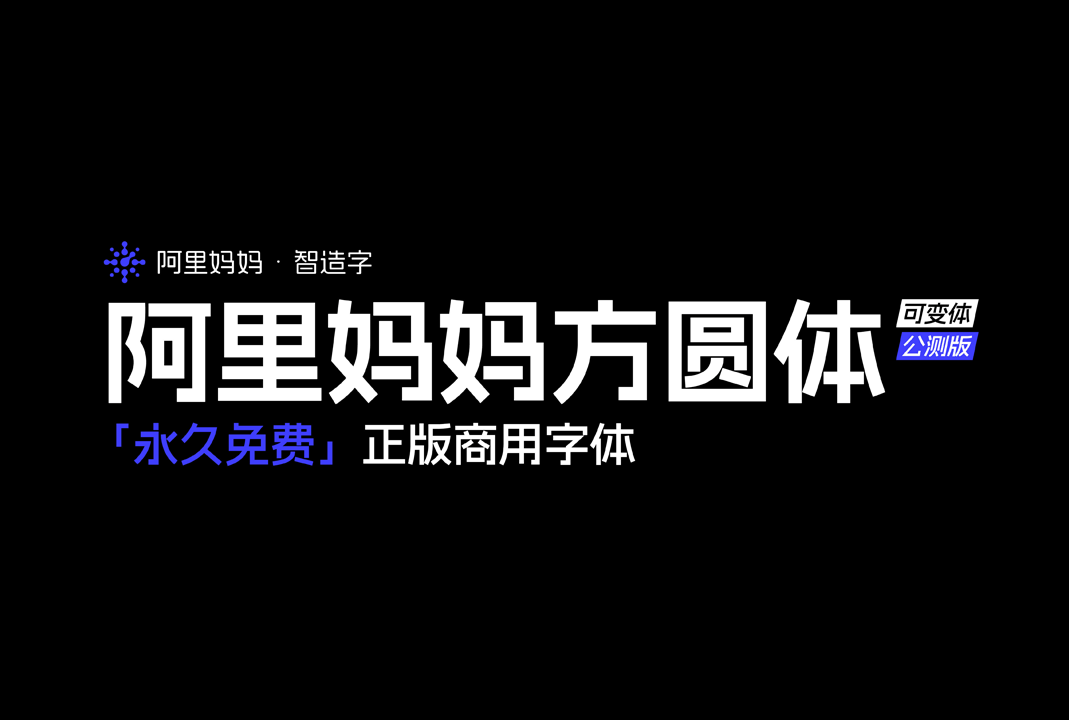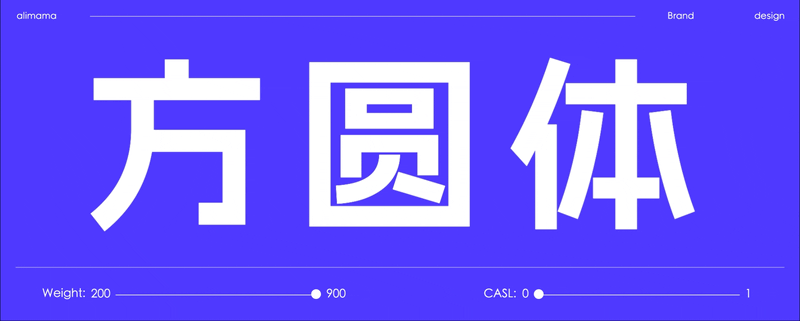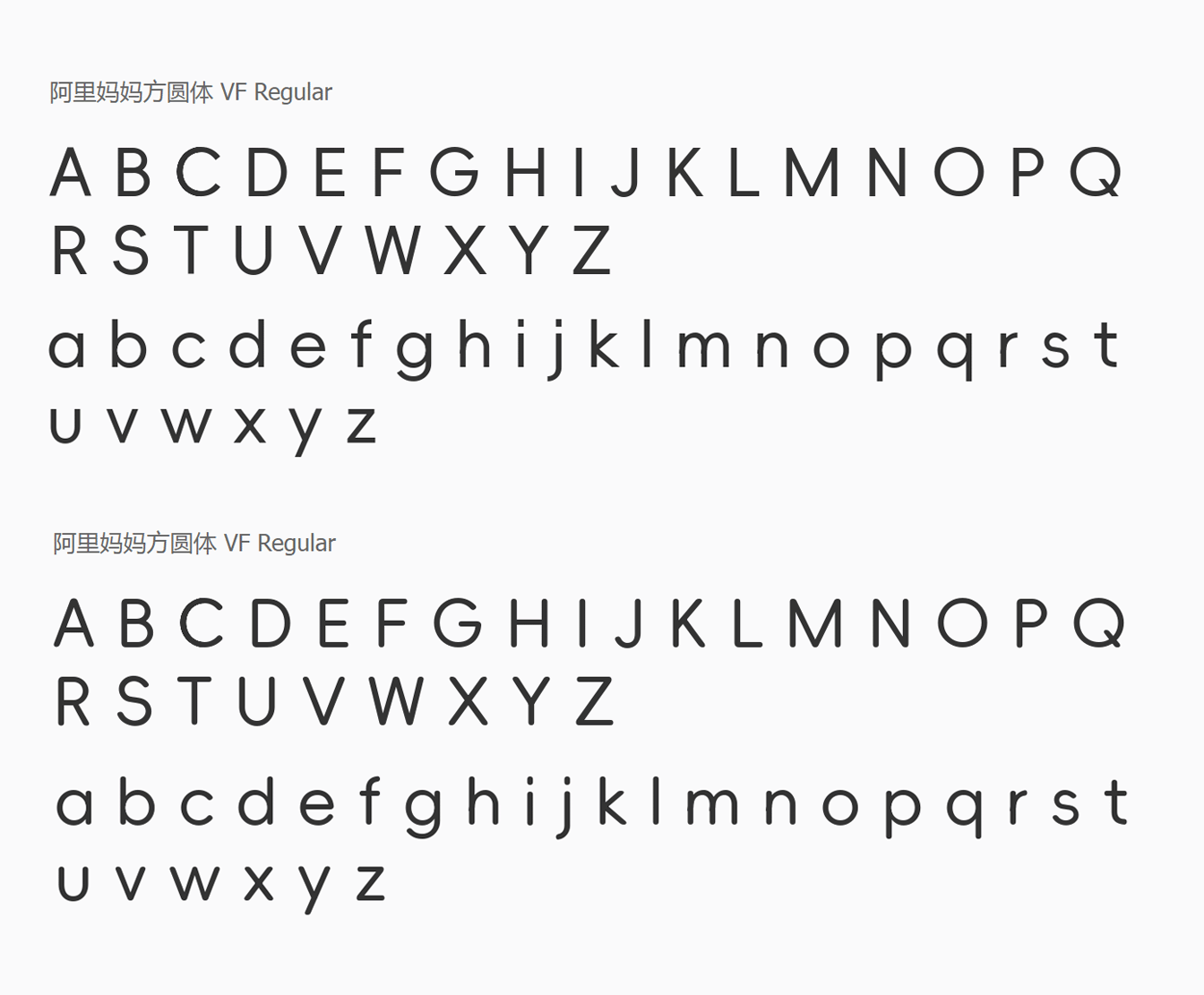
阿里妈妈方圆体(AlimamaFangYuanTiVF)是阿里妈妈·智造字通过智能AI的方式完成的一款简体中文双轴可变字体,其中字重和字型的双轴是可变的,可以实现不同尺寸的任意组合变化。
阿里妈妈的方圆体是一个中文简体字库,它由黑体和圆体两个字型的变轴组成,黑体中正,圆体灵动;收纳中文字符6763个汉字(包括但不限于GB2312);英文大小写共52个;常用标点符号共227个,总计7042个字符。